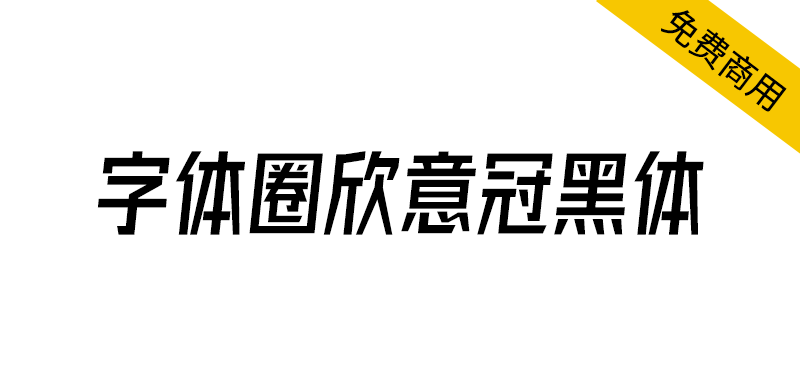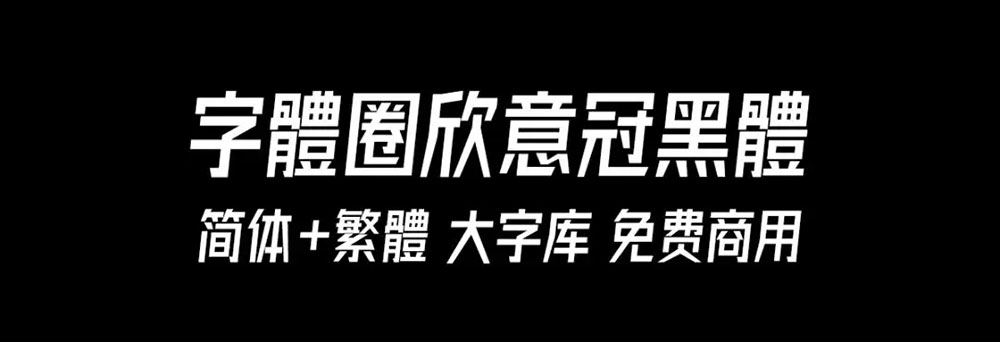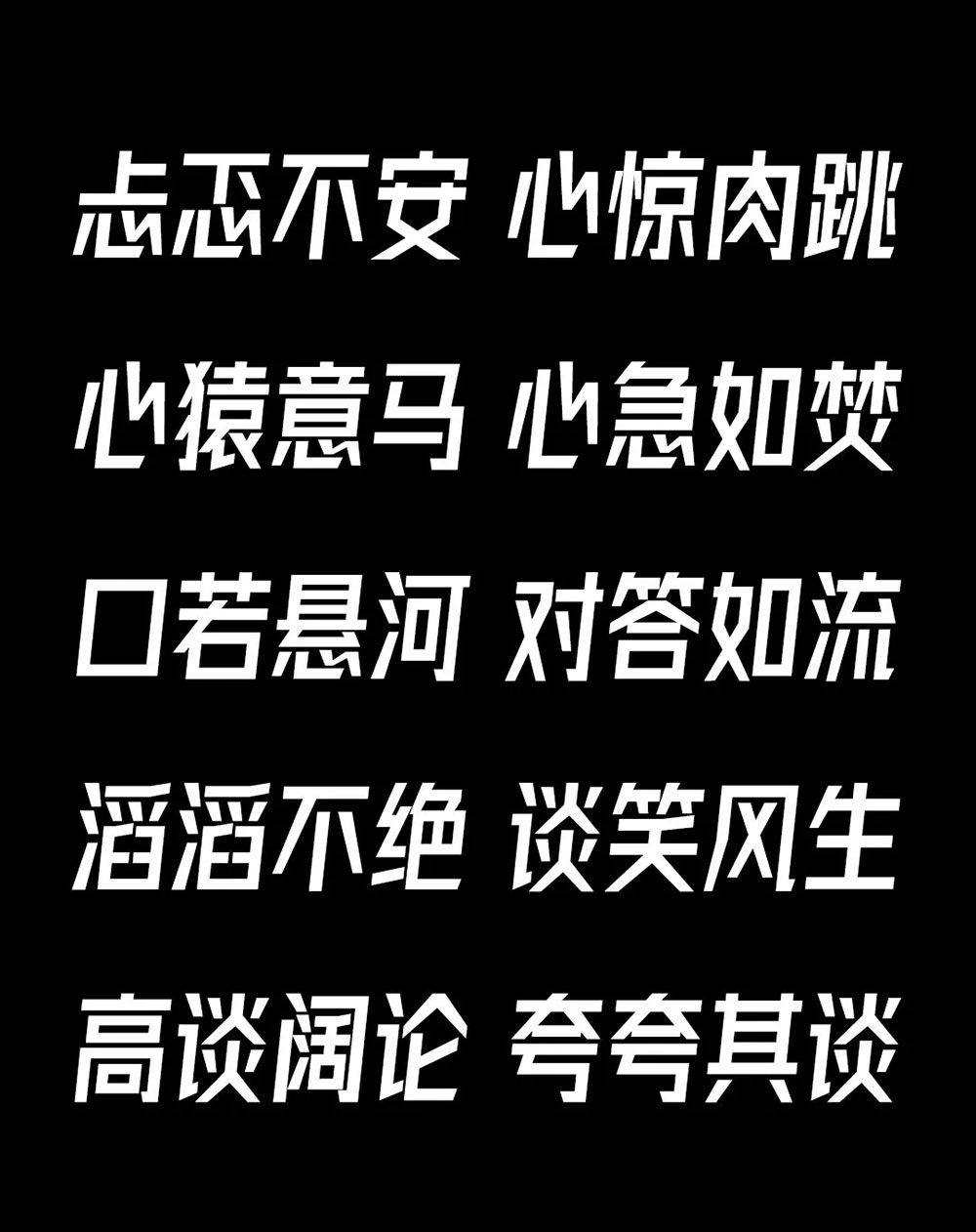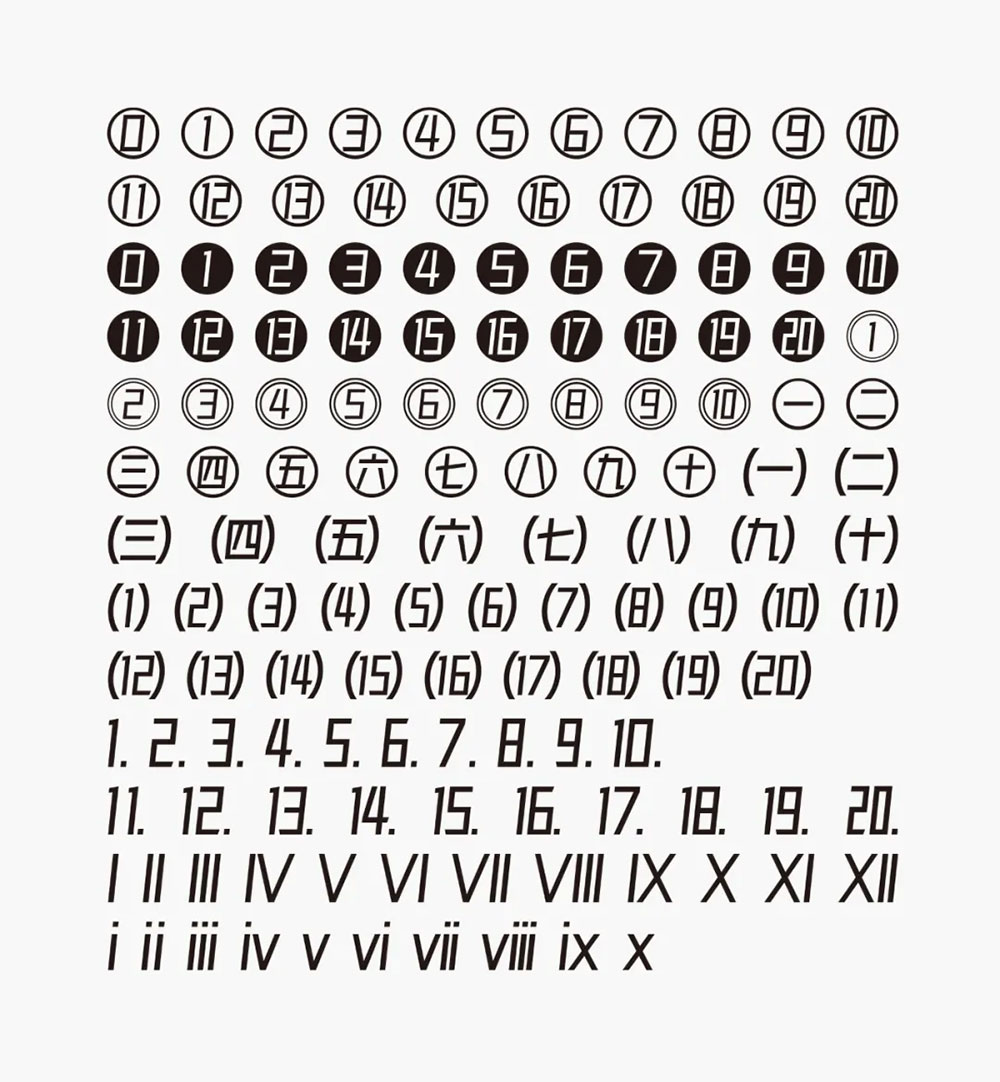
【字体圈欣意冠黑体】一套字形偏高瘦型、倾斜类字体
字体圈欣意冠黑体是一款具有速度感的斜体风格黑体字体,由设计师邹乐伟(字体圈)创作,涵盖国家GB2312标准的6763个中文字符,若干个中英文符号,按需添加若干个生僻字,中文汉字已涵盖高达 9864 字,简体和繁体基本都不缺字。字形偏高瘦型,字体倾斜6°,笔触粗实,具有很强的力量感和速度感。